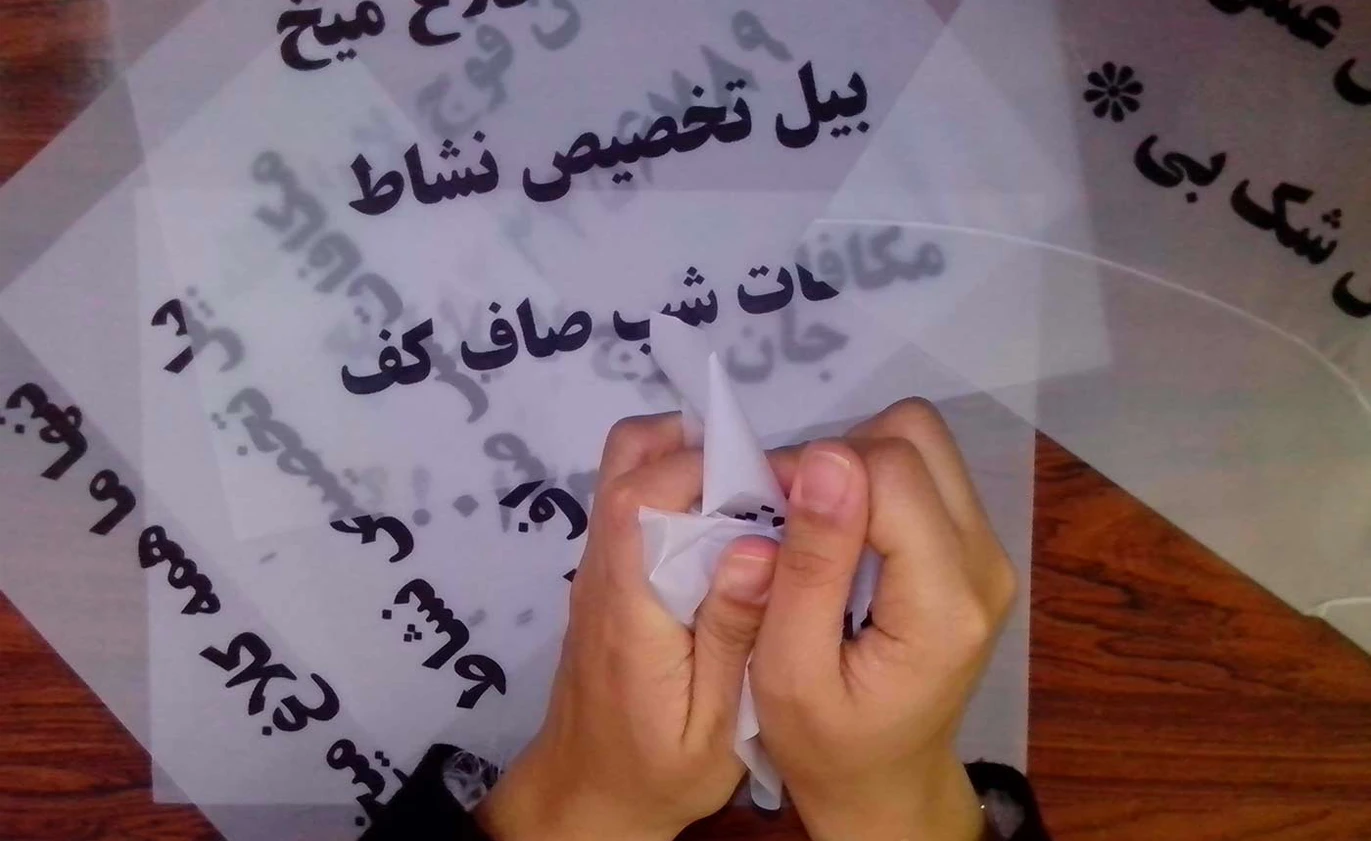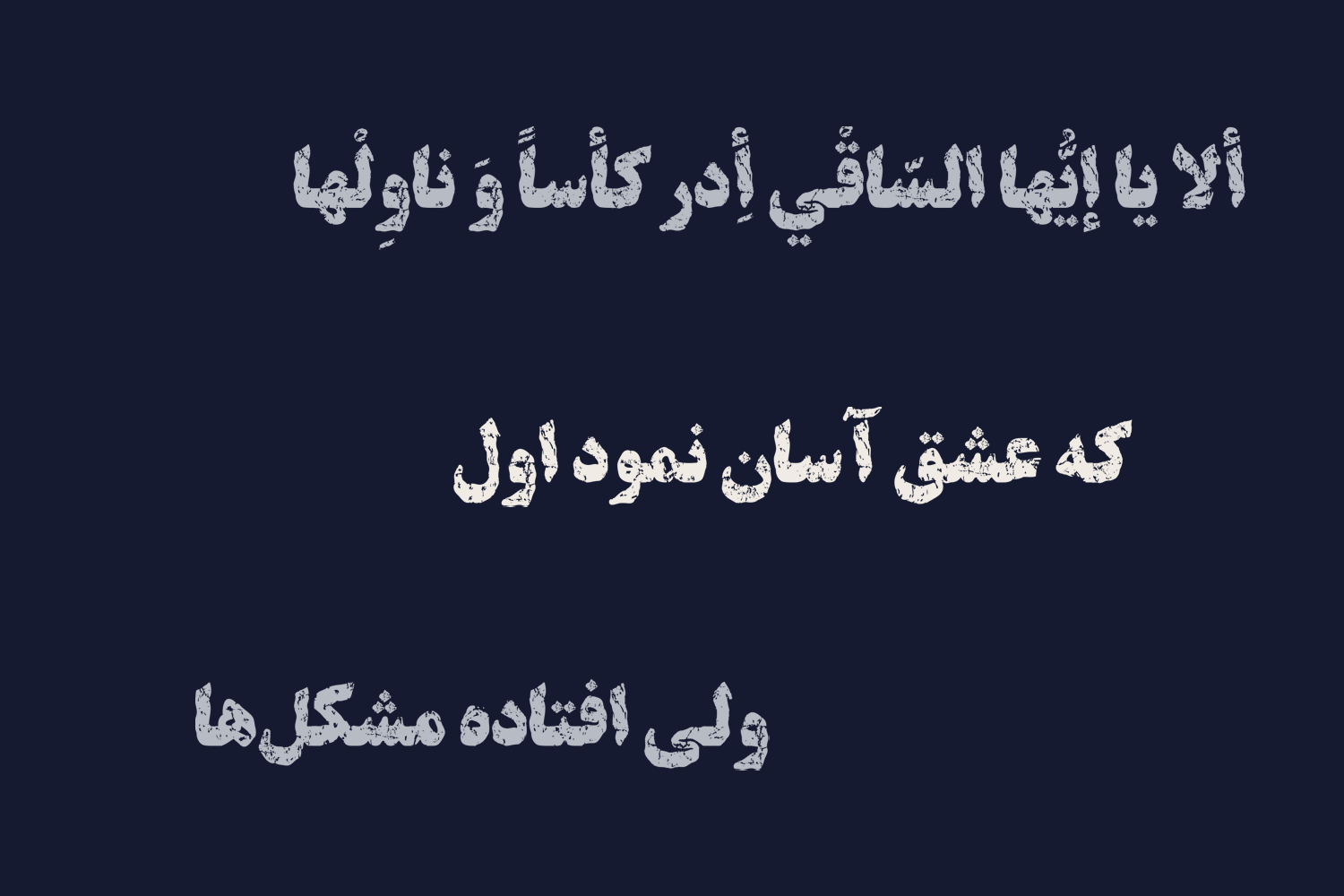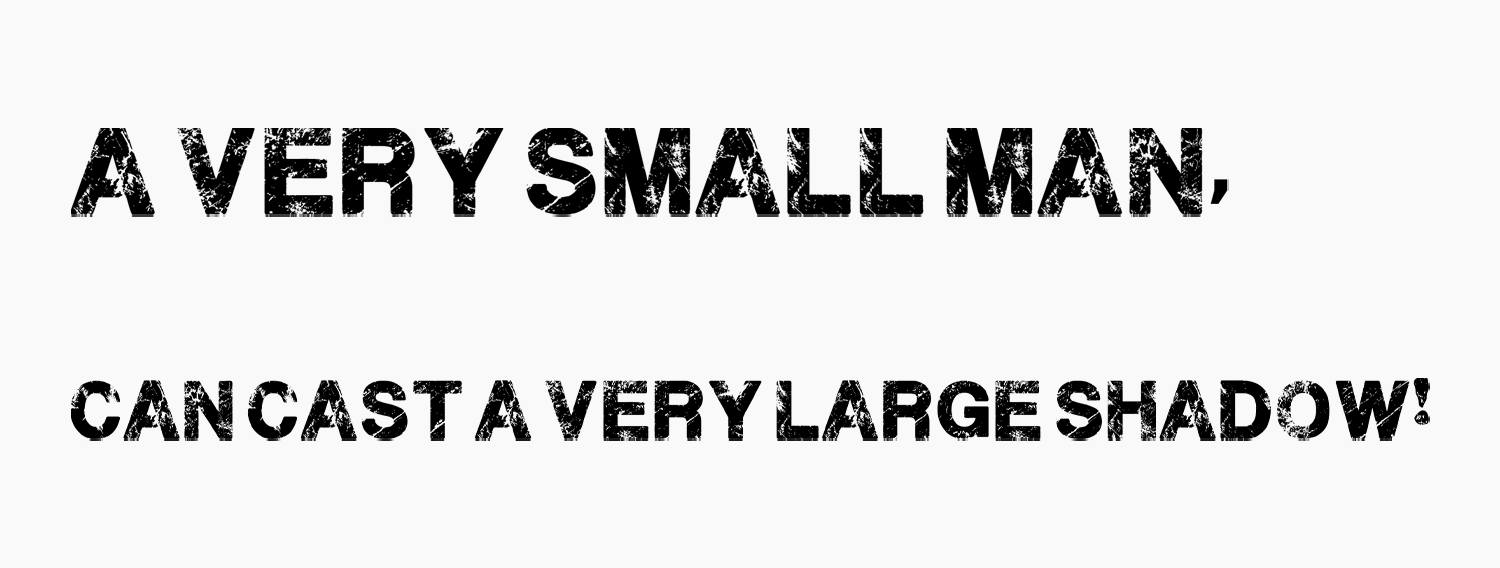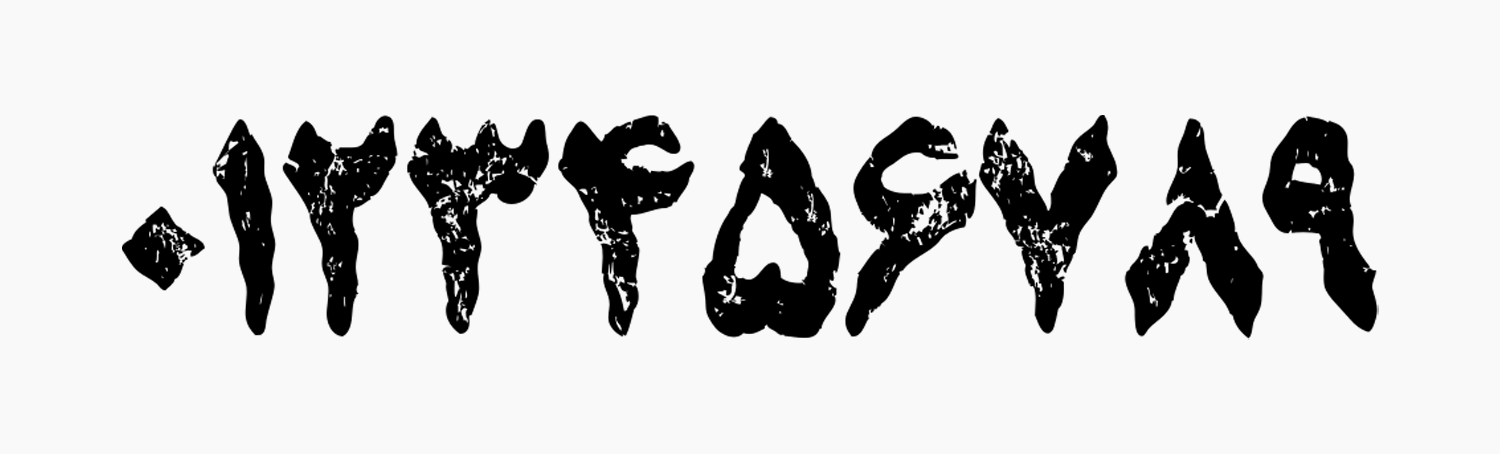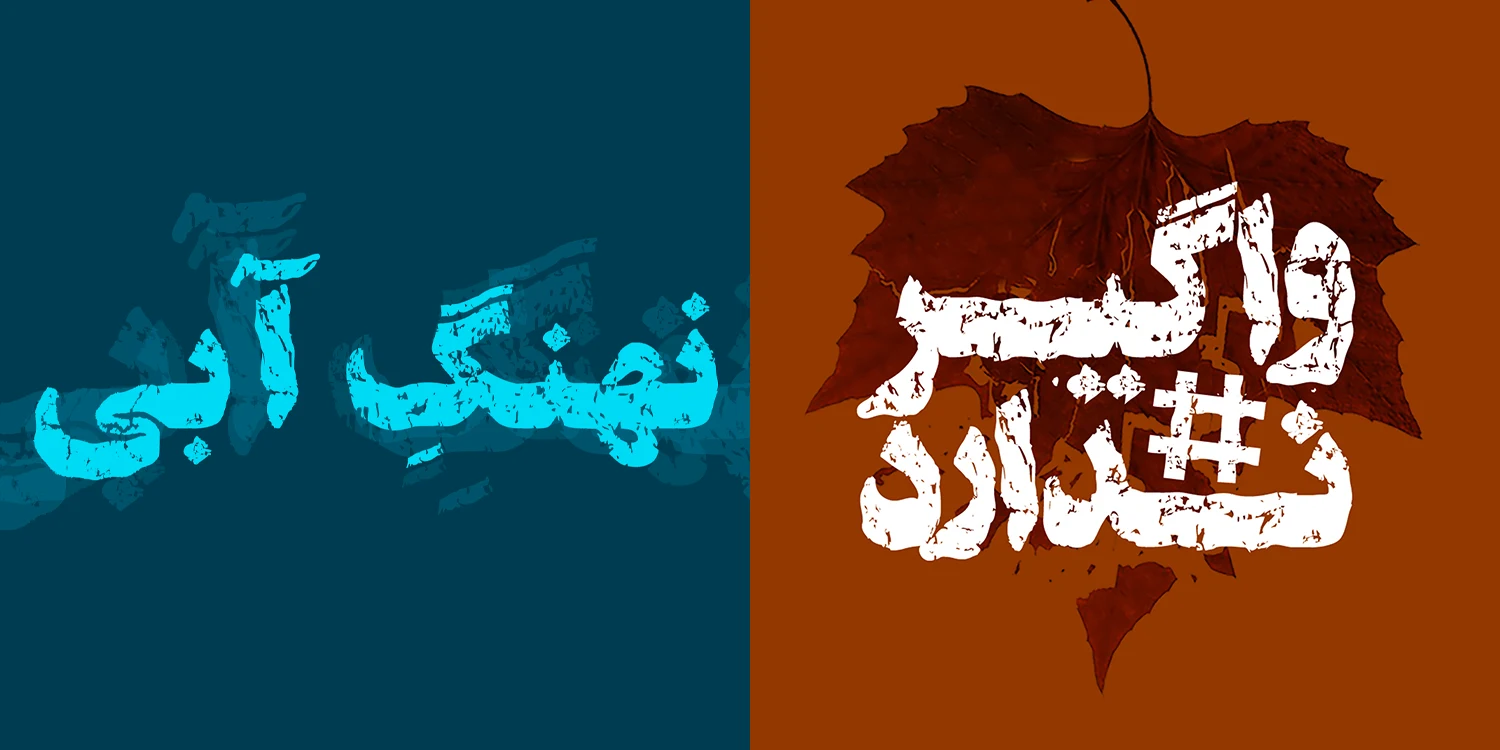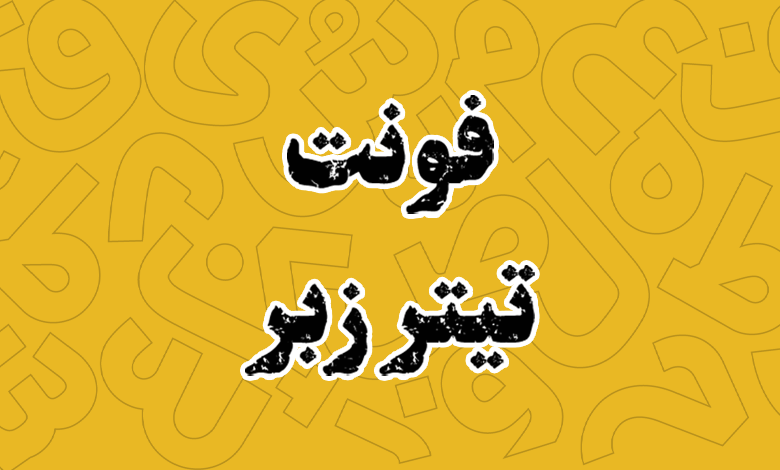
فونت تیتر زبر (Titr Zebr)
فونت تیتر زبر (به انگلیسی: Titr Zebr) یک فونت رایگان و نسبتا فانتزی است که با توجه به ضخامت و وزنی که برای حروف این قلم در نظر گرفته شده، میتوان از آن برای کارهای نمایشی و فونت عناوین استفاده کرد. این قلم از چندین زبان پشتیبانی میکند.
ملیحه نوازش پور این قلم را در قالب یک پروژه دانشجویی و در کارگاه طراحی فونت مسلم ابراهیمی در قالب یک تایپفیس طراحی کرده است که بر روی فونت تیتر کار شده است. هدف در این کارگاه این بوده که هر دانشجو با ایدهای خاص روی فونت دلخواهی کار کرده و یک تایپ فیس جدید را برمبنای آن خلق کند که برای فونت تیتر زبر، دانشجو از ایده ایجاد خطوط و نقاط گرافیکی افکتیو استفاده کرده است.
در ادامه این نوشته از سایت فونتچی به نقد و بررسی فونت تیتر زبر خواهیم پرداخت؛ فونتی که با توجه به ضخامت و سبک فانتزی که بر روی حروف فونت تیتر اعمال شده است، برای عناوین مناسب بوده و میتوانید برای کارهای گرافیکی که نیاز به یک قلم نمایشی دارید از آن استفاده کنید.
فونت تیتر زبر با ایجاد تغییراتی در فونت رایگان تیتر ایجاد شده است که این قلم از چندین زبان پشتیبانی کرده و دارای گلیفهای اختصاصی برای زبان لاتین انگلیسی هم میباشد.
سبک طراحی و وزن فونت تیتر زبر
در ساخت تایپفیس تیتر زبر دانشجو ابتدا حروف را که بر مبنای فونت تیتر بودهاند، بر روی کاغذ چاپ نموده است. سپس ایده وی این بوده که با مچاله کردن کاغذ باعث از بین رفتن چاپ در نقاط مختلف حروف شده و به اصطلاح حالت گرافیکی افکتیو روی فونت اعمال شود.
نتیجه آن ایجاد نقاط و خطوط نامنظم و در زوایای گوناگون چه در بخشهای درونی حروف و چه بخش بیرونی بوده است که باعث شکلگیری فونت تیتر زبر شده است که در تصویر زیر ایده طراحی را مشاهده میکنید.
در نهایت همین سبک بر روی حروف اعمال شده و در قالب فایل نرمافزاری توسط محمد الیکایی در قالب فونت توسعه داده شده است. برای این قلم یک فرمت TTF با وزن معمولی Regular در نظر گرفته شده است که برای تمامی زبانهای پشتیبانی شده فونت تیتر، همان سبک افکتیو لحاظ شده است.
پشتیبانی از چند زبان متنوع
فونت تیتر زبر از زبان فارسی پشتیبانی میکند که به لطف رسم خط فارسی بودن زبانهای مثل مثل عربی و کردی از آنها نیز پشتیبانی میکند. اما در مورد پشتیبانی سایر زبان ها کمی باید با تردید به این قلم نگاه کرد.
به عنوان مثال حروف «ی، ه، ؤ، ئ» در زبان عربی در این فونت پیادهسازی شده است اما حرفی مثل «ک» دارای گلیف نبوده و به صورت معمولی با فونت پیشفرض تایپ خواهد شد. یا در زبان اردو که حروف «ﮧ، ﮩ، ے» متفاوت از نسخه فارسی هستند، بهطور کلی فاقد گلیف است و باید صفحه کلید در حالت فارسی یا عربی باشد که از حروف این زبانها برای اردو استفاده کنید.
خوشبختانه از نظر پشتیبانی اعراب این قلم کاملتر است و بهسادگی میتوانید تمامی اعراب عربی را همراه با کاراکترهای «تشدید، سکون و همزه» طوری که همنشینی آنها با سایر اعراب موجب به هم خوردن چیدمان حروف نگردد استفاده کنید.
این قلم همچنین از زبان عربی پشتیبانی میکند به طوری که همان سبک گرافیکی افکتی که بر روی حروف فارسی اعمال شده بر روی آن پیاده سازی شده است.
دارای اعداد فارسی استاندارد
ویژگی دیگر این فونت رایگان پشتیبانی از اعداد فارسی استاندارد است. با قرار داشتن صفحه کلید روی زبان فارسی میتوانید از اعداد فارسی در این قلم استفاده کنید که نمونه صفر تا ۹ را در تصویر زیر میبینید.
اما در زبان عربی که اعداد «۴۵۶» دارای ظاهری متفاوت نسبت به «۴۵۶» فارسی هستند گلیف اختصاصی در نظر گرفته نشده است که یکی دیگر از کاستیهای این فونت است. پس لزوما در بخش اعداد برای زبان عربی نیز مجبور به استفاده از اعداد با تایپ فارسی خواهید بود.
مناسب عناوین و تیترهای نمایشی
فونت تیتر زبر یک قلم کاملا نمایشی بوده و با توجه به ضخامتی که در وزن معمولی برایش در نظر گرفته شده، مناسب عناوین است. بهترین کاربردی که این تایپفیس میتواند داشته باشد برای طراحی پوستر؛ بهویژه پوستر فیلم، موسیقی و بنرهایی است که جنبه تبلیغاتی یا اطلاعرسانی در قالب یک رویداد را دارند.
از دیگر کاربردهای این فونت میتوان به صنعت چاپ و مطبوعات اشاره کرد که برای چاپ جلد کتب با توجه به ضخامت و سبک فونت مناسب است. از کتاب گرفته تا طراحی انواع بروشور، مجلات و کتابهای مصور میتوانید از این قلم استفاده کنید تا افکت اعمال شده روی حروف در کنار وزن نسبتا چاقی که دارد، نگاه مخاطب را به خود جذب کند.
آخرین نسخه فونت تیتر زبر ۱.۱ است که چند سالی از انتشار آن میگذرد. از این قلم با توجه به وزن و سبک افکتیوی که دارد میتوانید برای عناوین و تیترهای نمایشی استفاده کنید. طراحی انواع پوستر، بنرهای تبلیغاتی و دعوت به رویدادها جزو مهمترین کاربردهای این قلم هستند.
هرچند که میتوانید استفاده مطبوعاتی از آن در صنعت چاپ بهویژه برای طراحی جلد کتب و مجلات نیز از این تایپفیس داشته باشید.